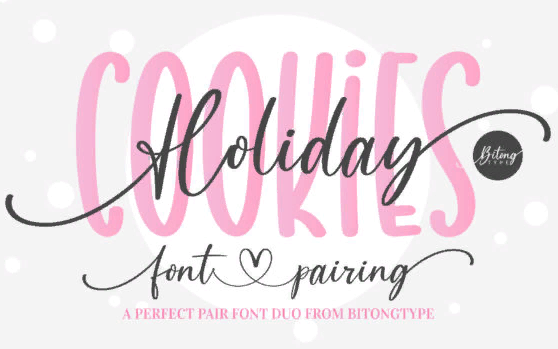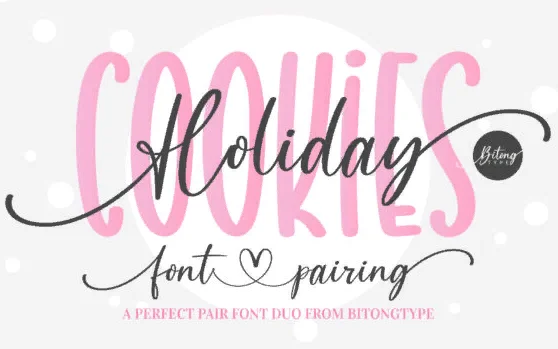
[Creativefabrica] Holiday Cookies Font (2021)
Название: Holiday Cookies Font (2021)
Holiday Cookies -
это дуо-стиль рукописного шрифта, который в равной степени очарователен и нежен.